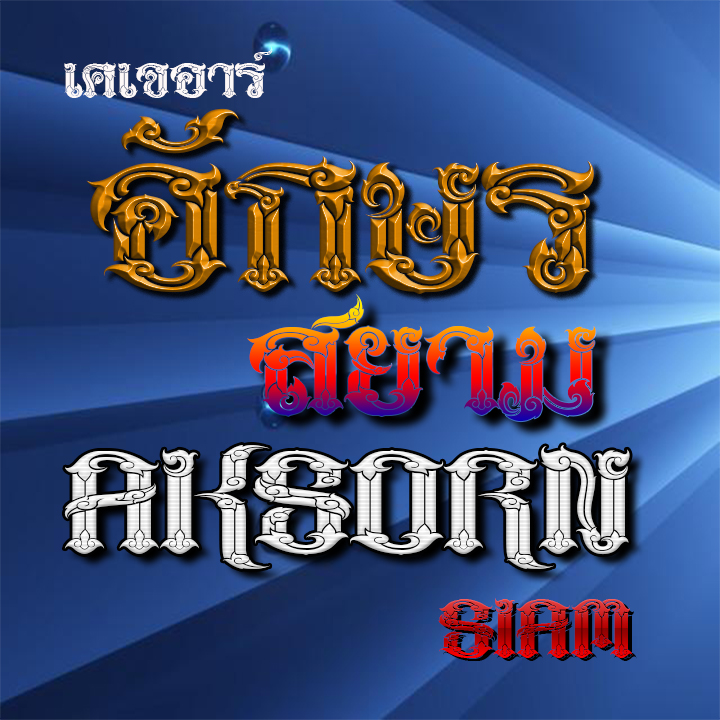
KJR AKSORN SIAM
เกือบ2เดือนกว่าจะสำเร็จได้ สำหรับฟอนต์ตัวนี้ อยากลองทำอะไรที่มันยากๆดู ซึ่งมันก็ยากจริงๆ
อาจไม่สมบูรณ์เท่าที่ควร เนื่องจากผมเองเขียนลายไทยไม่เป็น ก็เลยออกมาหน้าตาแบบนี้
ฟอนต์ชุดนี้มี2แบบ ตรงและเอียง มีทั้งไทยและอังกฤษ เลขอารบิคเลขไทย
ตัวนี้เป็นตัวทดลองนะครับ ยังไงก็ติดบัคครับ